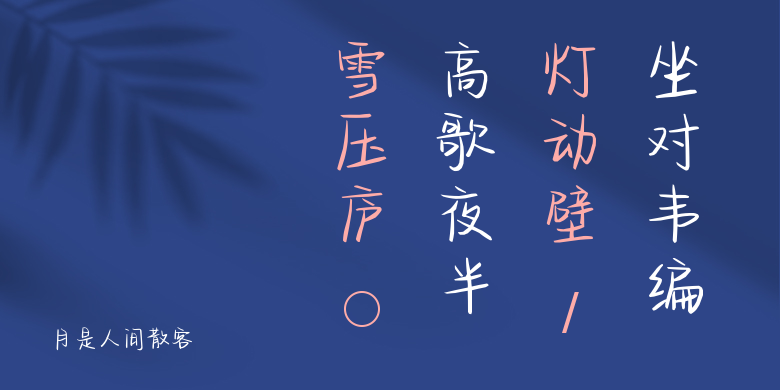
月是人间散客,这款字体结构工整、笔画清晰,兼顾美观与易读性,适用于标题、正文、海报、包装、LOGO 等多种场景。字形优雅稳定,风格百搭耐看,适配日常排版与创意设计,让文字呈现更舒适、更具质感。月是人间散客一笔一画,皆是细节,以均衡的比例、流畅的线条打造舒适视觉体验,字形端正大气,风格简约现代。无论是商业设计、品牌宣传还是日常排版,都能轻松驾驭,让文字更有格调与力量。月是人间散客字体下载。